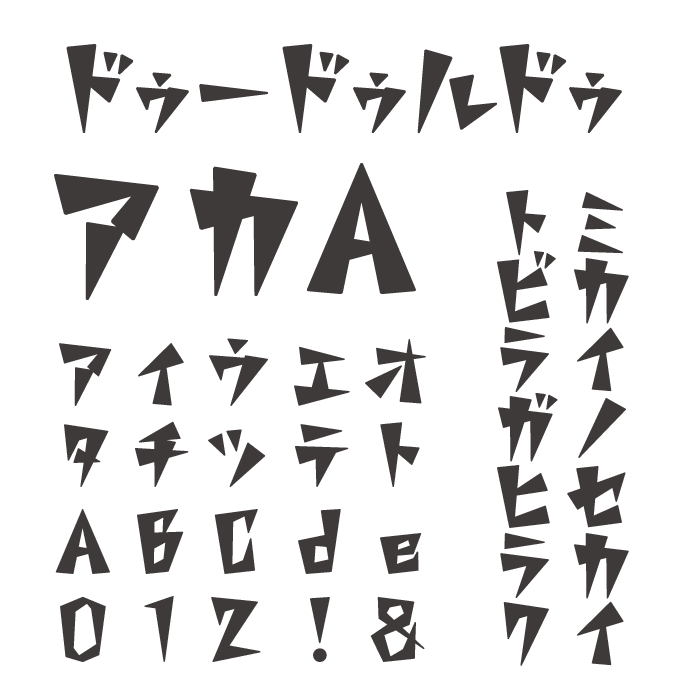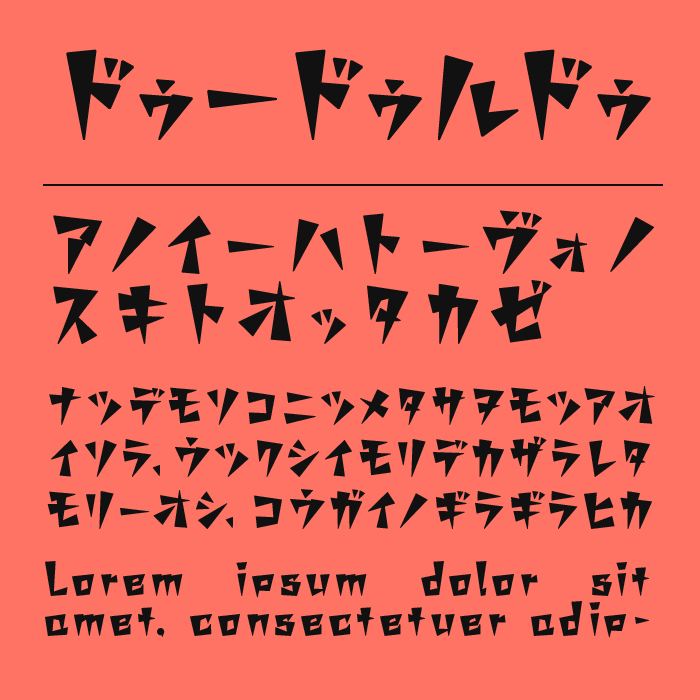
ドゥードゥルドゥは、鋭く尖ったシルエットと大胆な角度感が特徴的な、エネルギッシュなデザインフォントです。
紙を切り抜いたようなシャープな形状が並ぶことで、リズミカルで勢いのあるビジュアルを生み出しています。文字そのものがグラフィックのように見た目で、見るだけで強いインパクトを与えてくれるフォントです。
ロックテイストのロゴやアクション感のあるタイトル、ゲーム系ビジュアルなどと相性が良く、画面全体にスピード感を与えてくれます。荒々しさとスタイリッシュさを両立した、存在感抜群のフォントです。
収録文字は、カタカナ・アルファベット・数字・記号が収録。